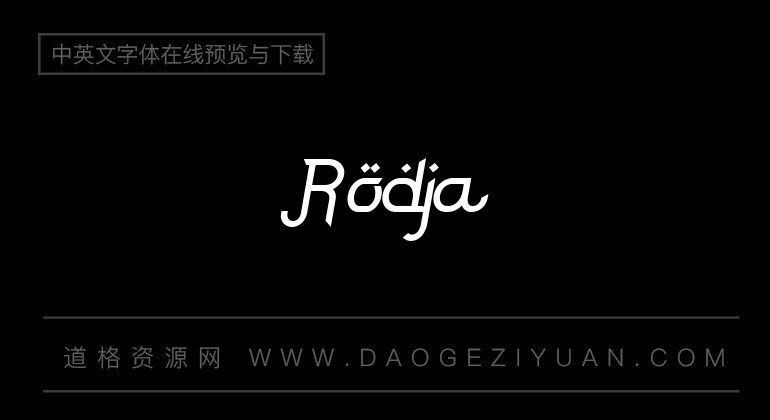
Rodja
Rodja 是一种免费的无衬线字体,由 Radomir Tinkov 设计。该字体非常适合用于标题和大号文本,其独特的设计风格使其在设计和印刷中特别显眼。Rodja 字体的字形结构简单,线条清晰,易于辨识和阅读。它拥有多种字重和风格,包括正常、粗体、斜体和粗斜体,适用于多种不同的设计需求。该字体支持多种语言,可在各种设备和平台上使用。总的来说,Rodja 是一种非常实用和优雅的字体,值得设计师和创作者们考虑使用。
Rodja是一款非常不错的手写艺术字体,具有很好的视觉感,适合于文化类的宣传设计、商业类品牌的广告和产品包装设计以及个性化文字排版等较多场景。